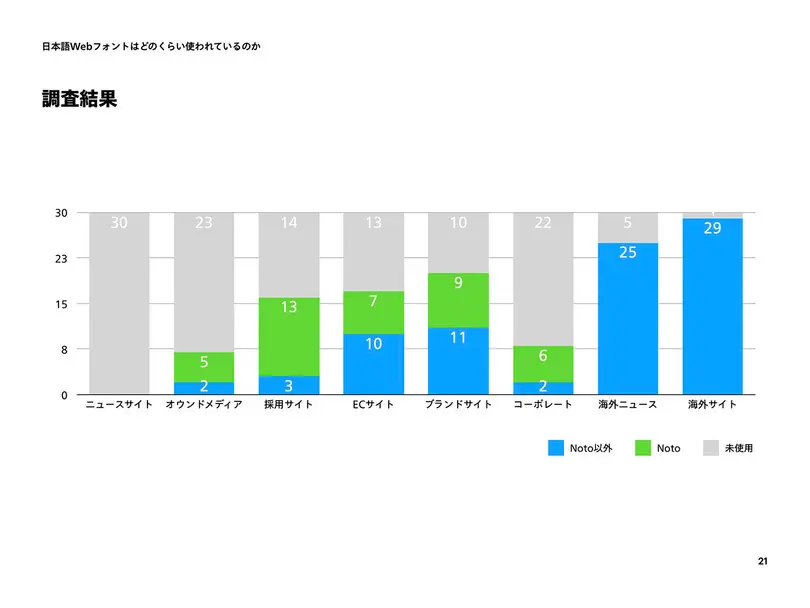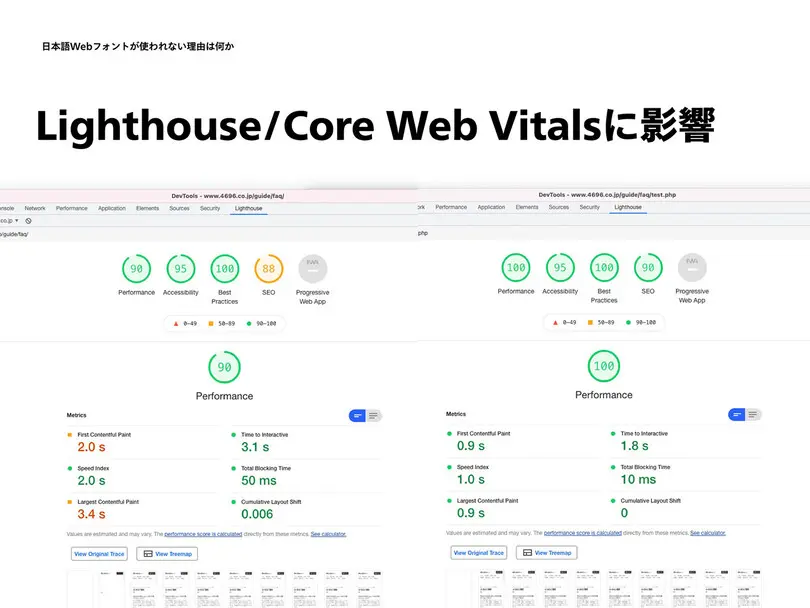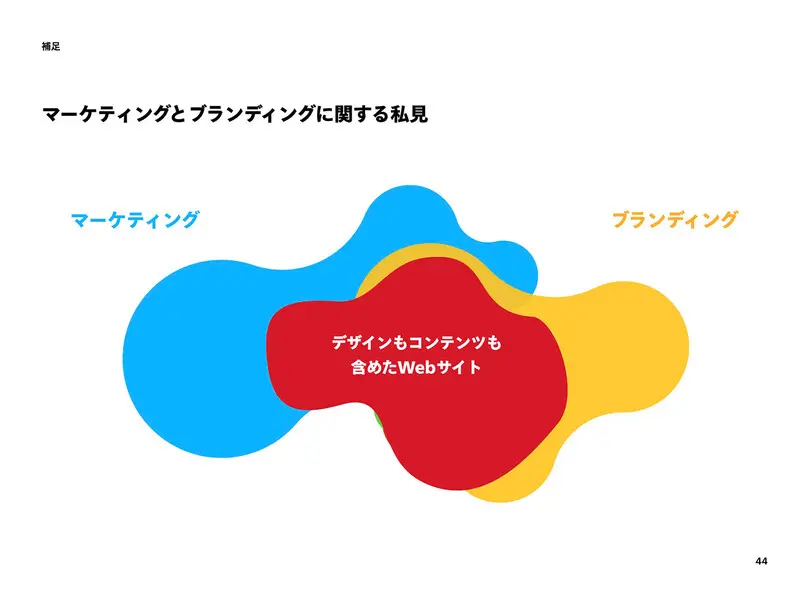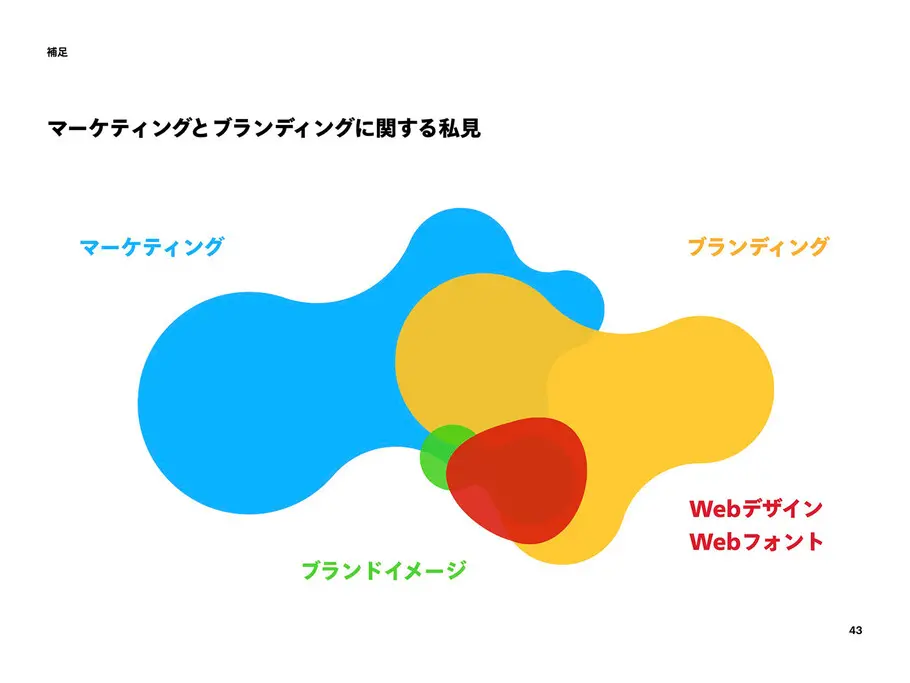
日本語Webフォントは必要か
株式会社シロクロのデザイナー、代表取締役として、Webサイトのマーケティング、営業、ディレクション、デザイン、実装業務などを担当している伊藤庄平氏によるプレゼンテーション。Web制作の現場で働く伊藤氏が日本語Webフォントについて解説。
日本語Webフォントはどのくらい使われているのか
伊藤氏は日本語Webフォントが実際どのくらい使われているのか、国内のWebサイトをカテゴリー別に調査をし、30件中どのくらいのWebサイトでWebフォントが使われているのかを調べました。
日本のサイト
国内のニュースサイト:0件
Webマガジンやオウンドメディア:7件
採用サイト:16件(Noto Sansが多い)
ECサイト:17件
ブランドサイト:20件
大手企業のコーポレートサイト:8件
海外のサイト
海外のニュースサイト:25件
一般的なサイト:29件
以下は、今回の調査結果をグラフにまとめたものです。やはり海外のサイトでWebフォントが多く使われているという結果でした。国内のニュースサイトでは、使用例が0件でしたが、他の採用サイトやECサイトでは予想以上にWebフォントが使われていました。ただし、Noto Sans(Googleが無料で提供しているWebフォント)を除くと、それほど多くない印象です。
日本語Webフォントが使われない理由は何か
Noto Sans以外の日本語Webフォントが使われない理由を考えたとき、いくつか理由があります。
一つは、契約の問題。大半のWebフォントサービスには定額料金がかかるため、受託会社のWebデザイナーがWebフォントを使いたいと思ったときに、制作会社のディレクター、企業の担当者、決裁者への確認が必要になります。そして、Webフォントが必要な理由を決裁者に説明しなければなりません。Noto Sansが使われているのは、無料で、契約も必要ないためと思われます。
Webフォントの利用費用は、平均するとおおよそ100万PV(ページビュー:そのWebページが見られた回数)で年間1万円くらいです。中小企業のサイトでは月2〜3万PV、それなりにうまくいっているオウンドメディアなどでは月20〜30万PVぐらいなので、Webフォントの使用は検討可能かと思います。また、欧文書体のWebフォントの場合、買い切りで1ウェイト39ドルぐらいで購入できて、PVに関係なく使えるサービスもあります。
Webフォントが使われないもう一つの理由が読み込みの問題です。Webフォントを使っているWebサイトにアクセスすると、まずシステムフォント(PCにあらかじめ入っているフォント)でページが読み込まれ、その後にWebフォントに切り替わるのですが、若干の時間差が生じているという事実は否めません。そのため、パフォーマンスやユーザーの体験に影響が出てしまいます。
ウェブサイト読み込みにどのくらい時間がかかるのか、LighthouseやCore Web Vitalsで調べることができます。こちらがその結果です。
同じページの計測結果で、左図がWebフォント利用、右図がWebフォントを使っていない時のデータです。図のようにWebフォントを使うとパフォーマンスに影響が出ています。特に、ECサイトでは、読み込み時間と購入に因果関係があるというデータが出ているので、改善して欲しいという依頼もあります。
日本語Webフォントに関しては、システムフォント(デバイスフォント)で問題ないという意見もあります。「技術的な問題も発生せず、ユーザーにとって見慣れた書体が表示されるシステムフォントが最善」という考え方も一つの正解でしょう。そして、その真っ当な理由がWebデザイナーからWebフォントを遠ざけています。
Webフォントならではのメリット
制作者側から見た場合のWebフォントのメリットは、システムフォント以外を選択でき、どの環境でも同じフォントで表示させることができることです。もう一つのメリットは、OpenType機能が使えることです。OpenTypeフォントに含まれる様々な字形や文字スタイル、例えば、合字、字形、カーニング、分数、数字が使えるようになります。フォントの字間情報を制御するプロポーショナルメトリクス(font-feature-settings:“palt”)を使うと、自動で文字詰めすることも可能です。
反対に、ユーザー側から見た場合、Webフォントにはどのようなメリットがあるのでしょうか。Webフォントを使うことによって読みやすくなるのかどうかを考えたとき、フォントよりも組版の影響の方が大きく、Webフォントの選択は読みやすさに直結しません。また、クライアントに対するメリットを考えた場合でも、Webフォントを使って売り上げやPVが増えたという具体的事例は見つかりませんでした。
マーケティングとブランディング
次に、ウェブサイト制作におけるマーケティングとブランディングについて考えてみましょう。例えば、旅行に行こうと思ったときに、ある高級旅館の名前が思い浮かんだとします。そして、その旅館のWebサイトを見て、家族全員の宿泊料金を調べます。この場合の旅館の名前を思いついたところがブランディングの領域で、実際に申込や購入につながるところがマーケティングの領域です。
また、ブランディングに付随するブランドイメージもあります。例えば、高級旅館の名前を思い出したときに、思い浮かぶビジュアルがブランドイメージです。その旅館のWebサイトを見たときに、すごくダサかったら、「イメージと違う」と思うでしょう。ブランディングには、ブランドイメージという視覚的な印象がつきまといます。
WebフォントやWebデザインは、ブランディングやブランドイメージ寄りのところをカバーできるものです。デザインだけ変えても効果はなく、内容を変え、さらにデザインも変えることで初めて効果があるのです。
つまり、Webフォント単独では、マーケティングやブランディングにおける直接的な効果は少ないのです。ただし、ブランドイメージ定義にWebフォントは必要であり、ブランディングを行う際には有効であると言えます。
Webサイトを使って購入や契約をするときに、Webデザインの品質や方向性は判断材料にならないのですが、そのサイトにデザインが施されていない場合、機会損失が発生している可能性は否定できません。つまり、Webデザインだけで、マーケティング効果を伸ばすことは難しいのですが、Webデザインがないとマーケティング効果が下がる可能性は大いにあるということです。
まとめ
コンテンツをビジュアルと合わせてブランドイメージを定義したいときにWebフォントは必要になります。文章に湿度感、リズム、雰囲気を持たせたいときに効果があります。ただし、ニュースサイトなど、コンテンツをそのまま提供したい場合、Webフォントがノイズになる可能性もあるのです。
今はまだ課題がありますが、技術的な問題は今後改善されていくでしょう。Webサイトから提供される情報は多種多様を極めます。適切にかつ伝わりやすくするための技法として、マーケティングやデザイン的なアプローチとともに、Webフォントの活躍が増えることを期待しています。